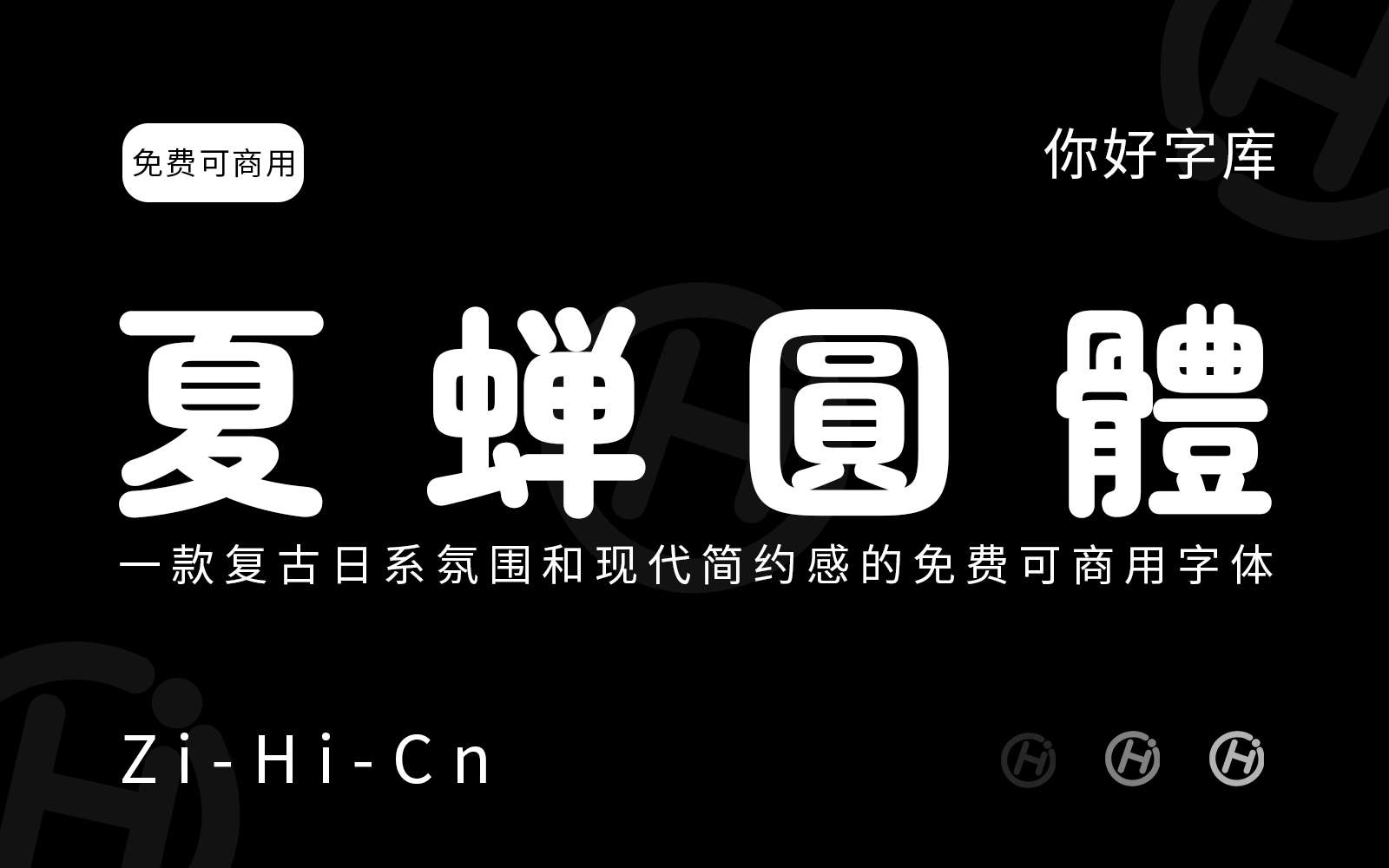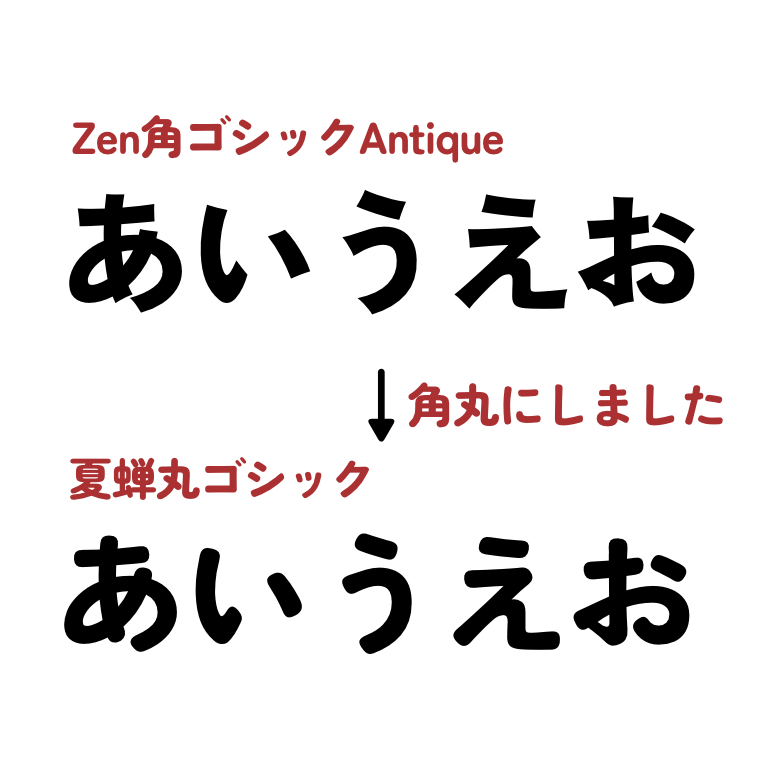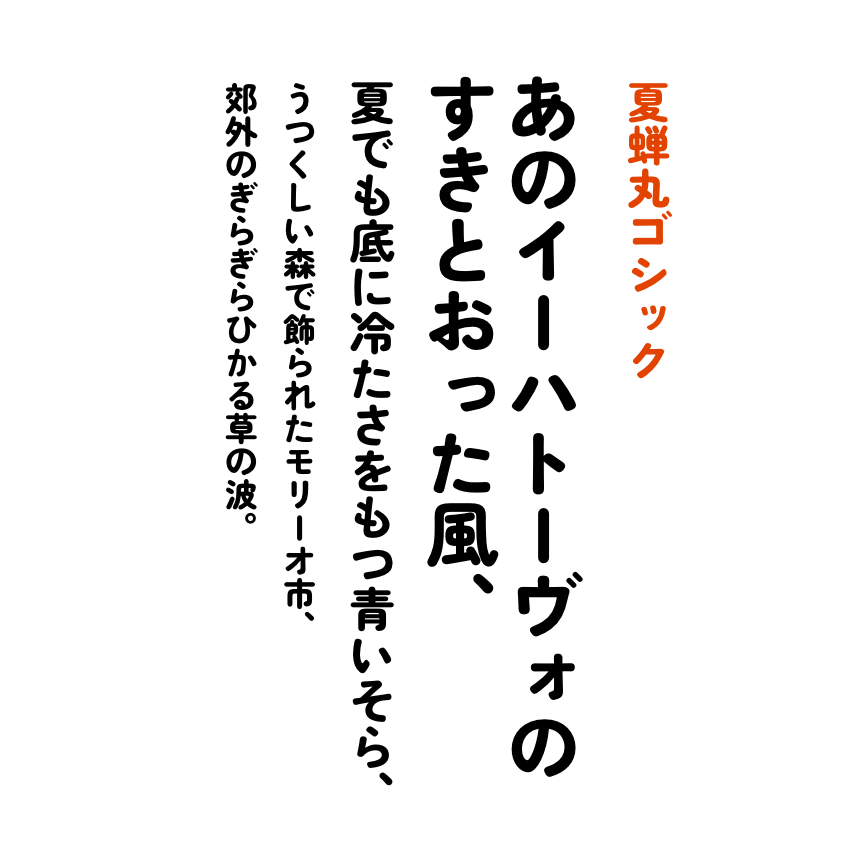
夏蝉圆体
字体简介
“夏蝉圆体”(日文名:夏蝉丸ゴシック)是一款由日本设计师基于 Zen 角ゴシック Antique 和 Zen 丸ゴシック合并改造的免费开源中文字体,发布于2023年5月。它属于无衬线圆体风格,字形圆润饱满,融合了复古日系氛围和现代简约感,笔画粗细均匀,略带几何感。这款字体包含约7000个字符,支持简体中文、繁体中文、日文假名及基本拉丁文字符,覆盖GB2312标准。